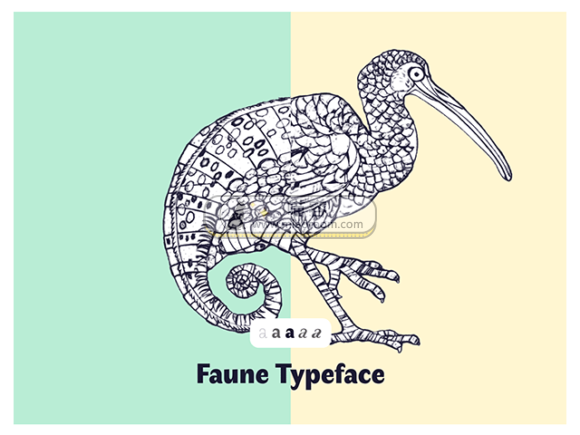
[系统字体] 一款灵感来自动物的字体 资源介绍参数 资源类别: 实用素材 如遇问题: 联系客服/留言反馈 下载地址: 前往下载 实用素材 精美字体 21年1月19日 编辑 前往下载 喵容发布2号 取消关注 关注 私信 本文分享的一款字体(faune)。这款字体是由Alice Savoie在国家艺术中心与Groupe Imprimerie Nationale合作委托的背景下创建的的。该字体灵感来源于动物,并以两部伟大的历史作品为基础。可以说是一款具有独特意义的字体。 相关文章: [系统字体] 一款“狂野”风格字体系列:本文介绍的字体——Sonder是一款适用于徽标设计和大型游戏的字体。它有serif和sans-serif版本(即衬线字体和无衬线字体),同时它包括了两个样式(粗糙和常规)。该字体免费个人使用,商用需要购买哦! 下载 …... [系统字体] 复古脚本字体:本文介绍的是一款具有复古外观的脚本字体——Buffalo。它是品牌和标志设计的理想选择,有需要的朋友可以到文末下载哦! 下载权限查看 ¥ 免费下载 评论并刷新后下载 登录后下载 查看演示 {{attr.name}}: 您 …... [系统字体] 几何无衬线字体——NOAH:今天分享的一款系统字体NOAH具有细节清晰,布局独特的优点。它能够满足所有的印刷要求,如果需要的朋友可以到文末下载哦! 下载权限查看 ¥ 免费下载 评论并刷新后下载 登录后下载 查看演示 {{attr.name}} …... [系统字体] 一款装饰性极强的字体——Moalang:今天分享的是一款装饰性非常强的一款字体——Moalang。它由印度尼西亚的字体设计师Agga Swist’blnk设计并且免费用于个人和商业用途! 喵容——Moalang字体1喵容——Moalang字体2 下载权限查看 ¥ 免费下载 …... [系统字体]优雅现代手写英文字体 Domillion字体:资源名称 Domillion 资源大小 591kb 资源格式 ttf、otf 资源简介 Domillion是海报,签名,标识,报价,专辑封面,名片,产品设计等的完美选择!该字体免费供个人使用! 喵容——Domillion-Brush-Font1喵容——D …... [系统字体]优质的装饰字体——Sabrva:资源描述 字体 资源名称 Sabrva 资源格式 ttf 资源大小 7.35kb 资源简介 Sabrva是完美字体的选择,可在 – 水印,签名,摄影,徽标,名片,报价,专辑封面使用。免费供个人使用! 喵容——Sabrva1喵容—— …... 下载权限查看 ¥ 免费下载 评论并刷新后下载 登录后下载 查看演示 {{attr.name}}: 您当前的等级为 登录后免费下载登录 小黑屋反思中,不准下载! 评论后刷新页面下载评论 支付¥以后下载 请先登录 您今天的下载次数(次)用完了,请明天再来 支付积分以后下载立即支付 支付以后下载立即支付 您当前的用户组不允许下载升级会员 您已获得下载权限 您可以每天下载资源次,今日剩余次 声明:本文为原创作品,版权归作者所有。未经许可,不得转载或用于任何商业用途。如若本站内容侵犯了原著者的合法权益,可联系我们进行处理。 给TA打赏 共{{data.count}}人 人已打赏 faune动物字体下载